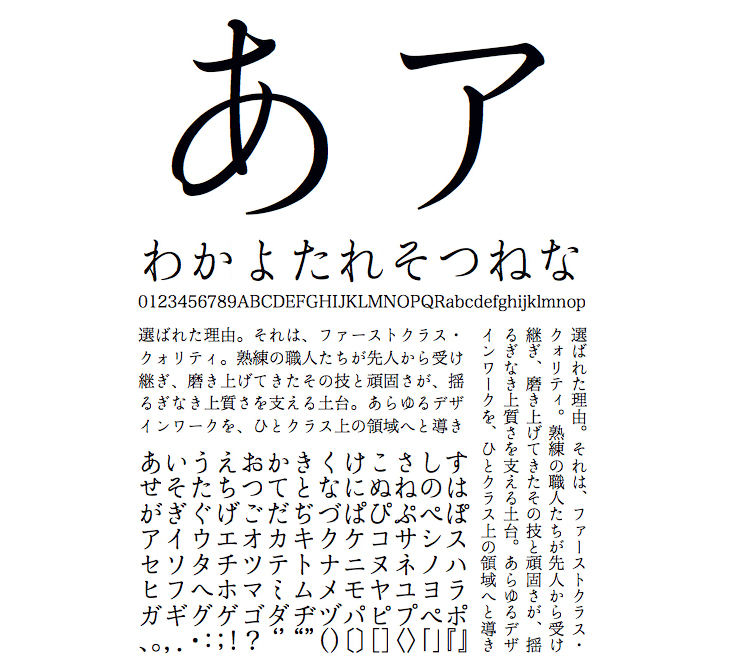
仮名・英数字グリフのみ収容
※本商品は仮名書体です。ギャラリーの見本に含まれる漢字はヒラギノ明朝を使用しています。
【游築(ゆうつき)36ポ仮名】明治から大正にかけて作られた築地活版製造所の36ポイント明朝体に着想を得て、元の書体の字面の大きさ、太さ、筆法などの調整を行いました。「ヒラギノ明朝体」の表情をよりクラシカルにする仮名書体です。
游築36ポ仮名 W2